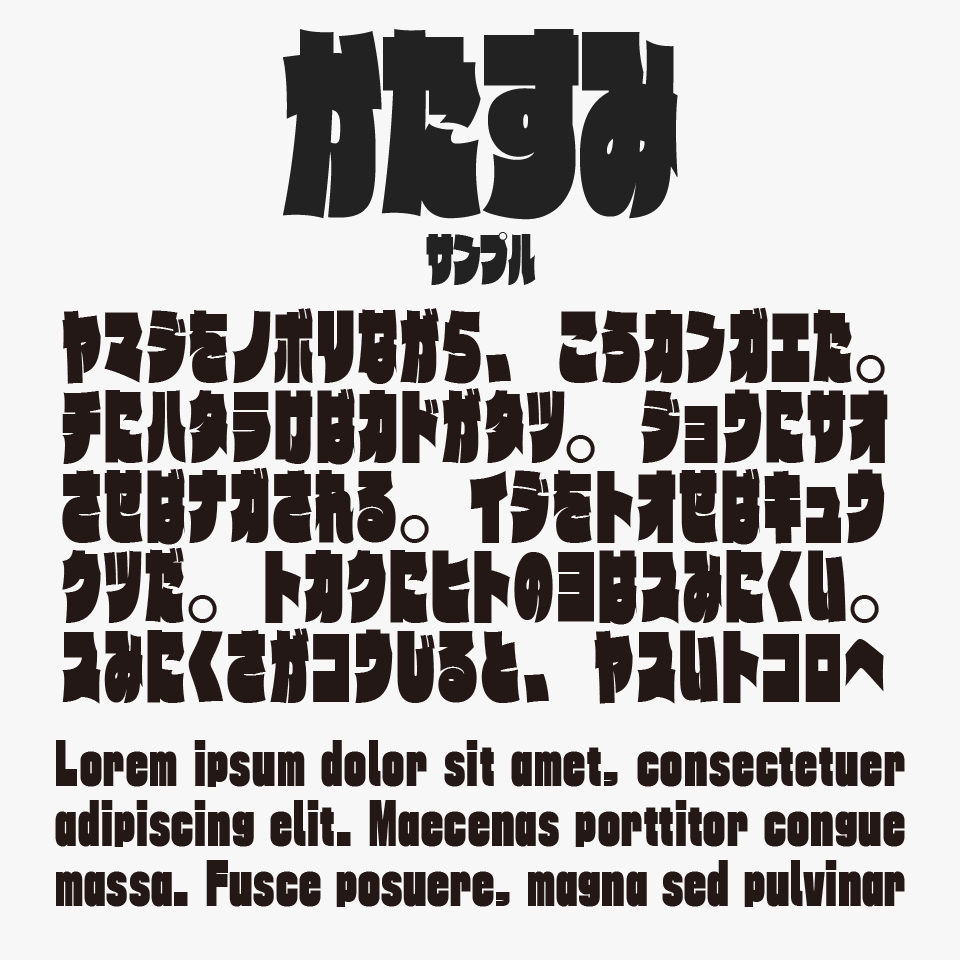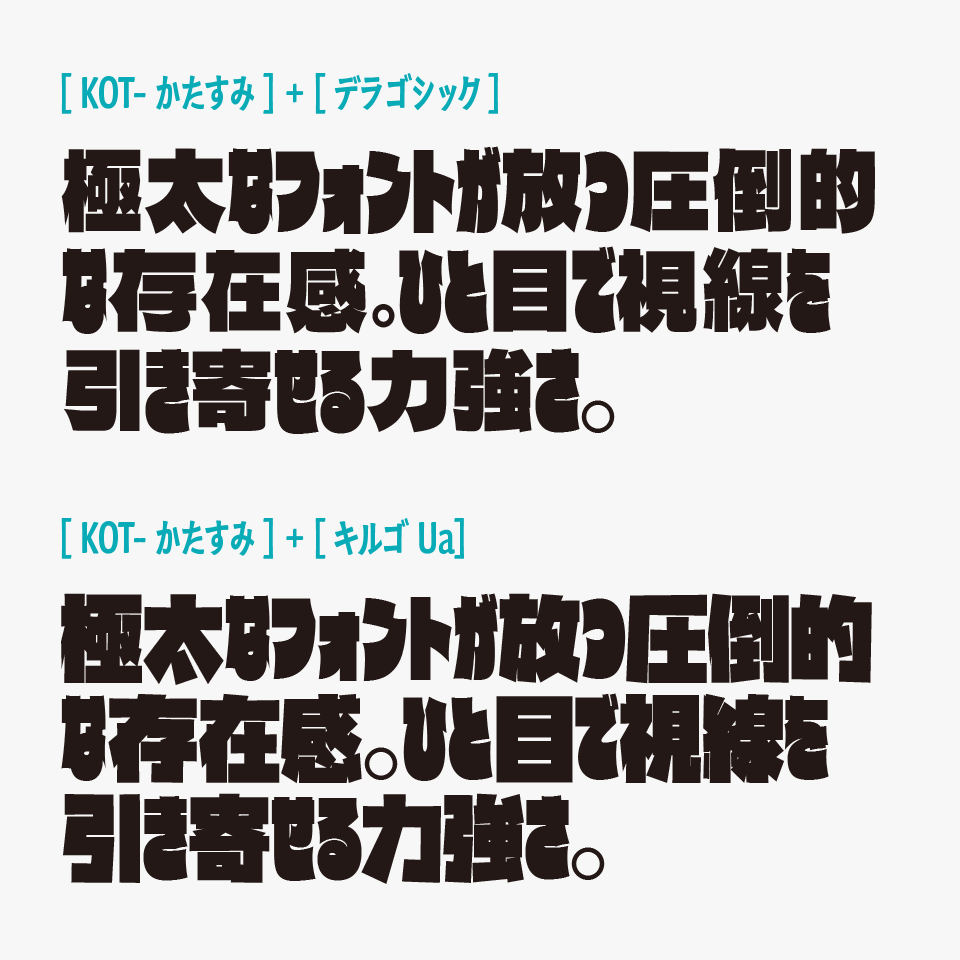
かたすみフォントは、ドドンとパワフルで、線先が直角ではなく少しエッジのあるフォルムがかっこいい超極太長体のゴシックフォントです。
均一ではない太さや、欠けたようなエッジが特徴で、少しクセになるような力強い印象を与えるフォントです。見出しに使うと文字がひとつの塊のように見え、ドッシリとした重厚感もしっかりと感じられます。
かたすみ
かなフォントのため、漢字は収録がないため、他の極太フォントと混植して使ってみたも面白いかもしれません。
以下の事例では「デラゴシック」や「キルゴ」と混ぜてみましたが、他にもマッチするフォントがあるので、いろいろ試してみると楽しいフォントです。
かたすみ